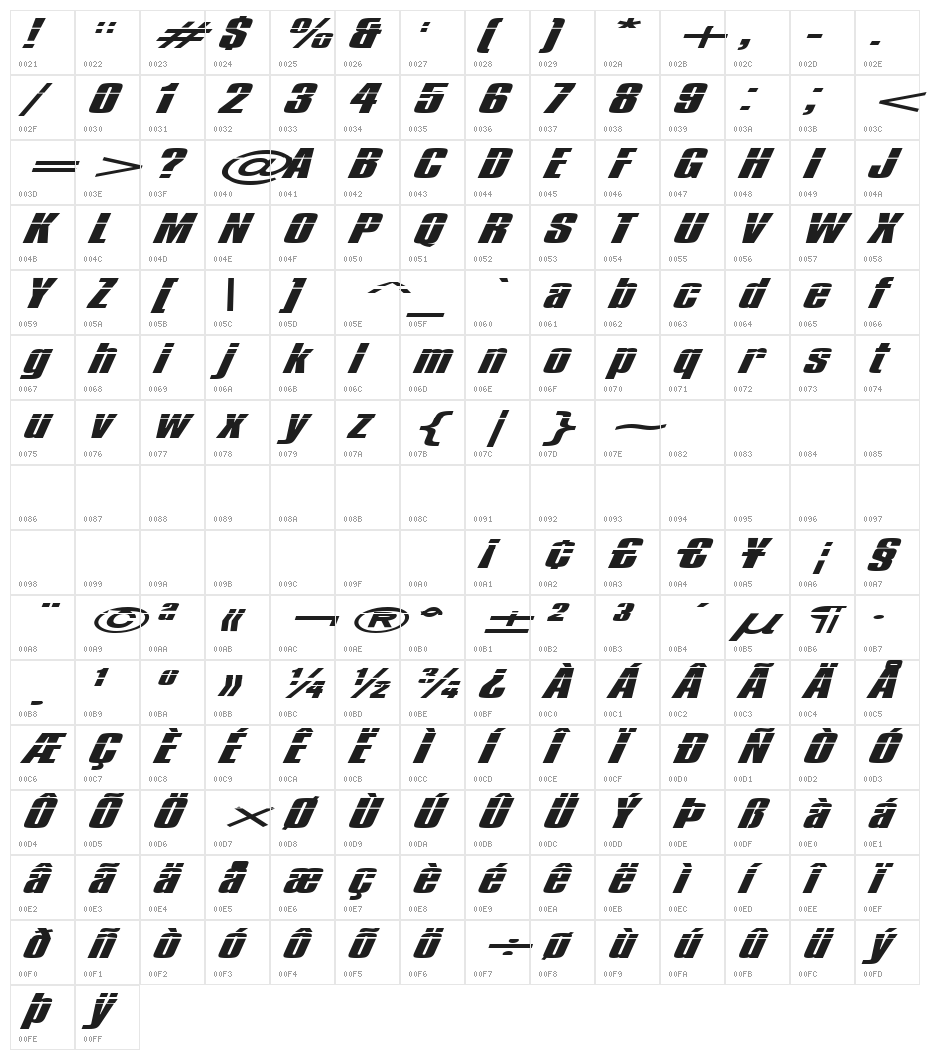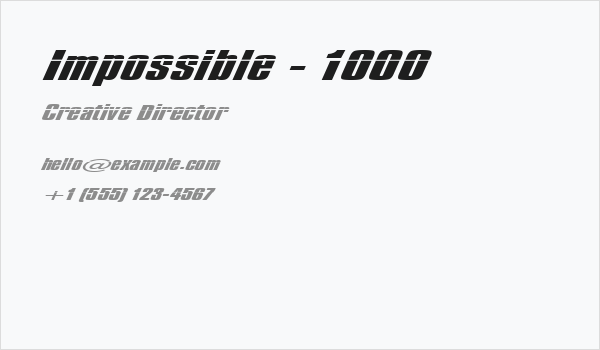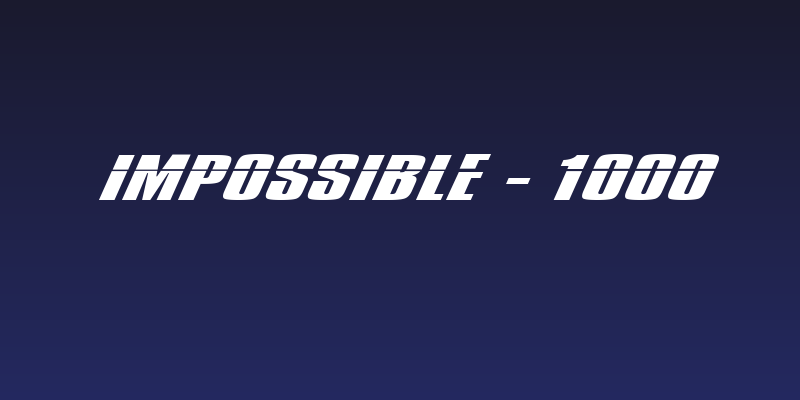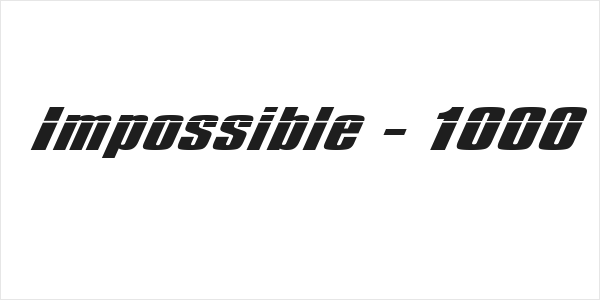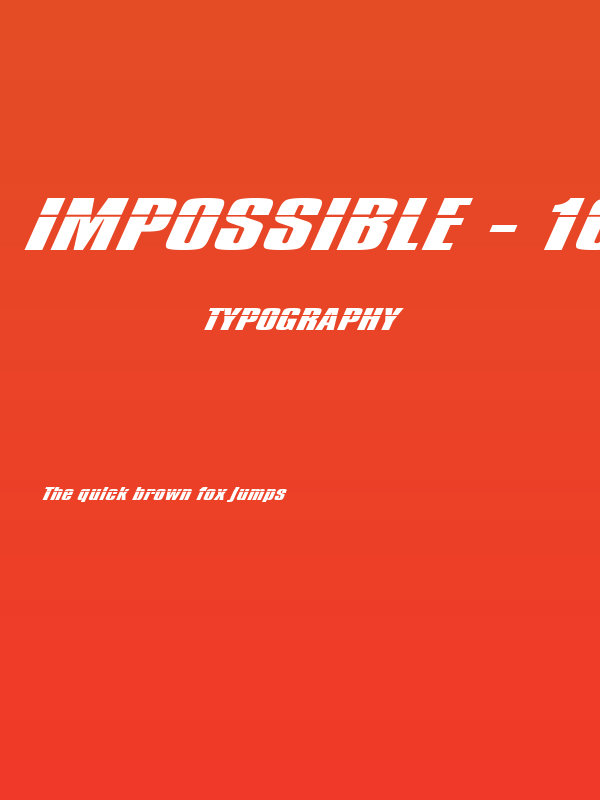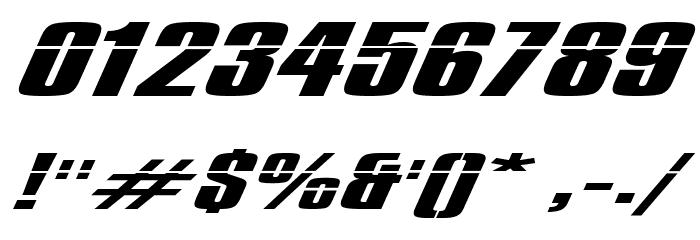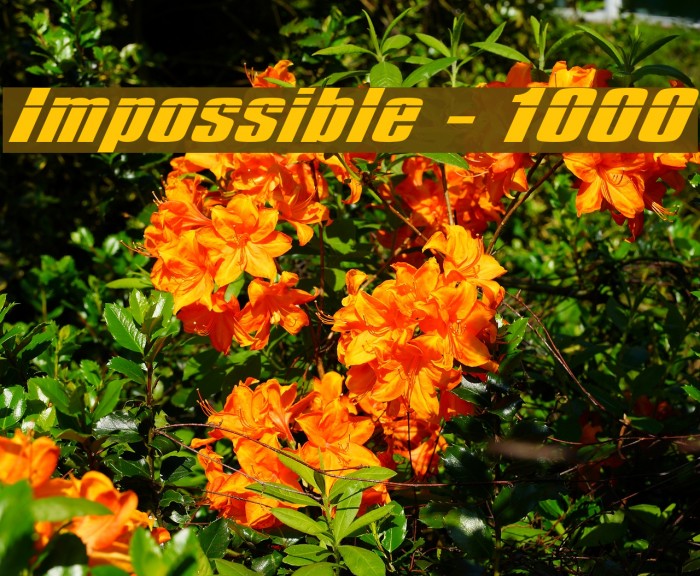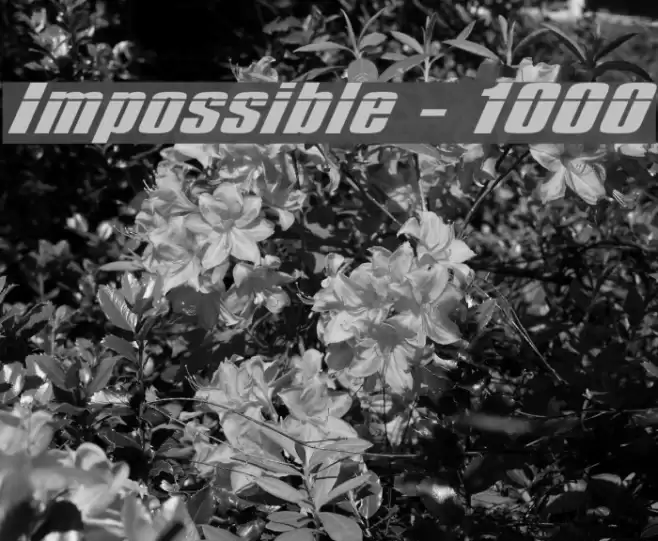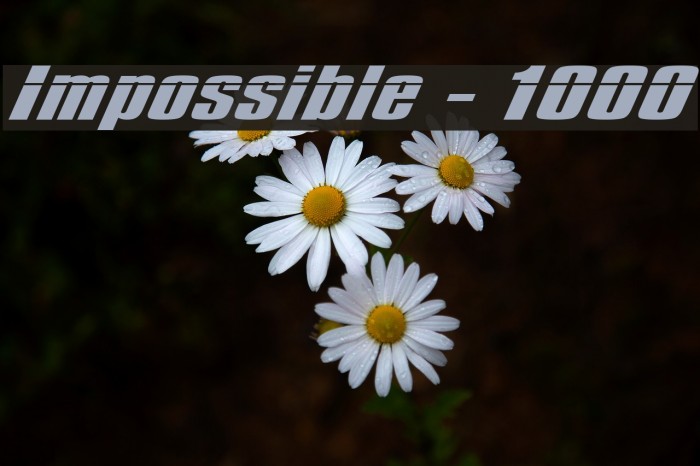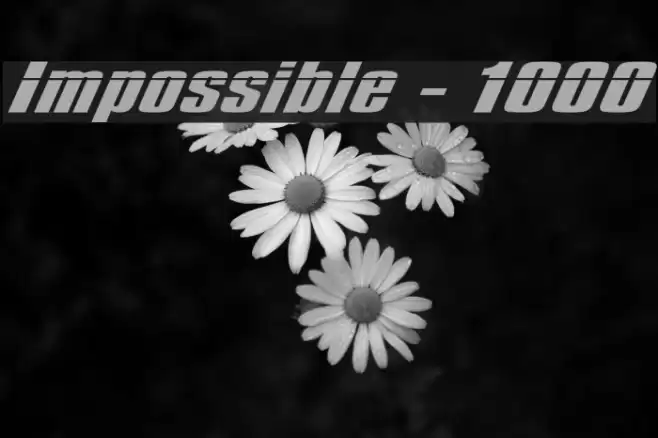
Impossible - 1000 Font
IMPOSSIBLE-1000 Litere mari
IMPOSSIBLE-1000 Litere mici
IMPOSSIBLE-1000 Alte caractere
| Proiecte propuse | Ideal for sports branding, dynamic posters, automotive advertisements, and any project needing a strong, energetic typeface. |